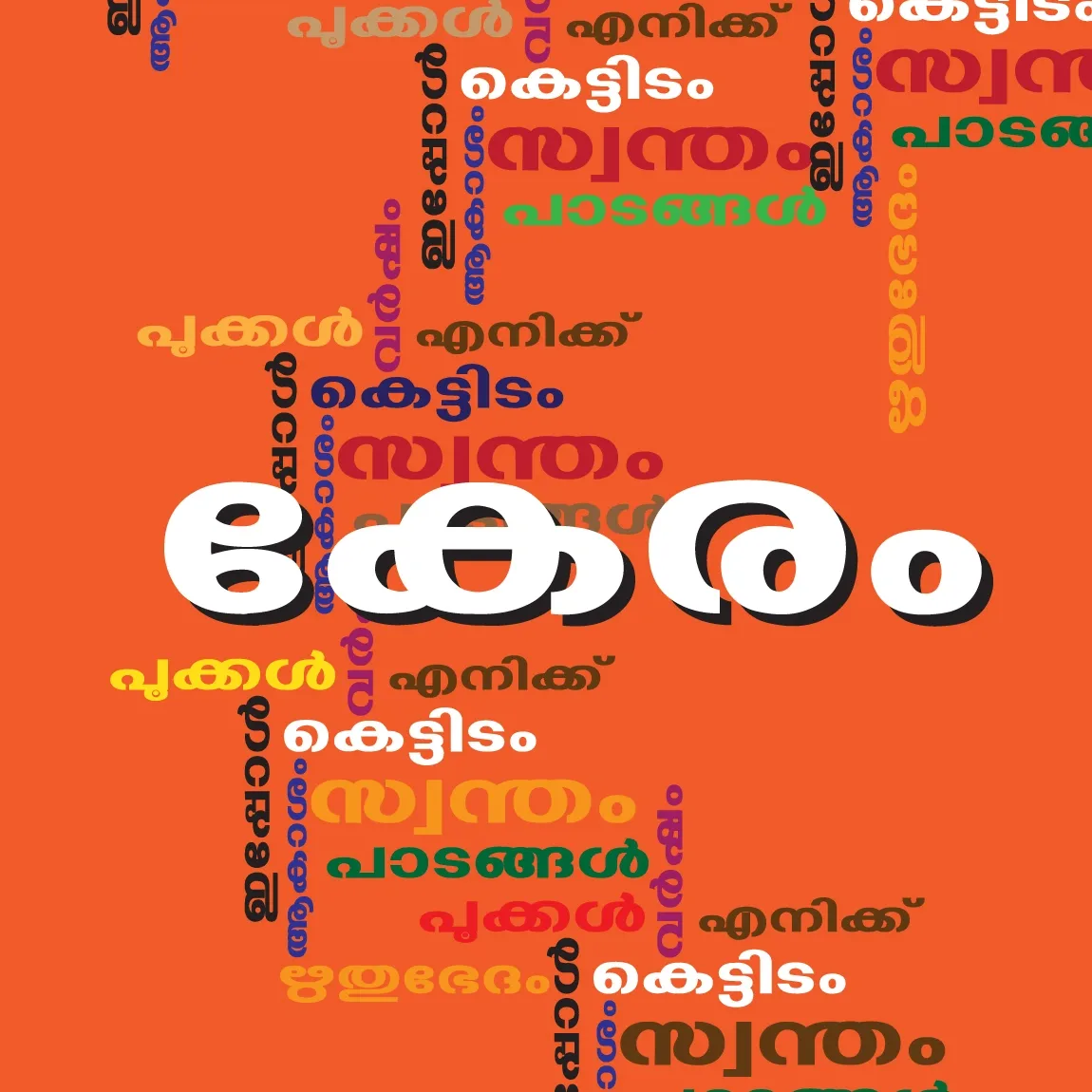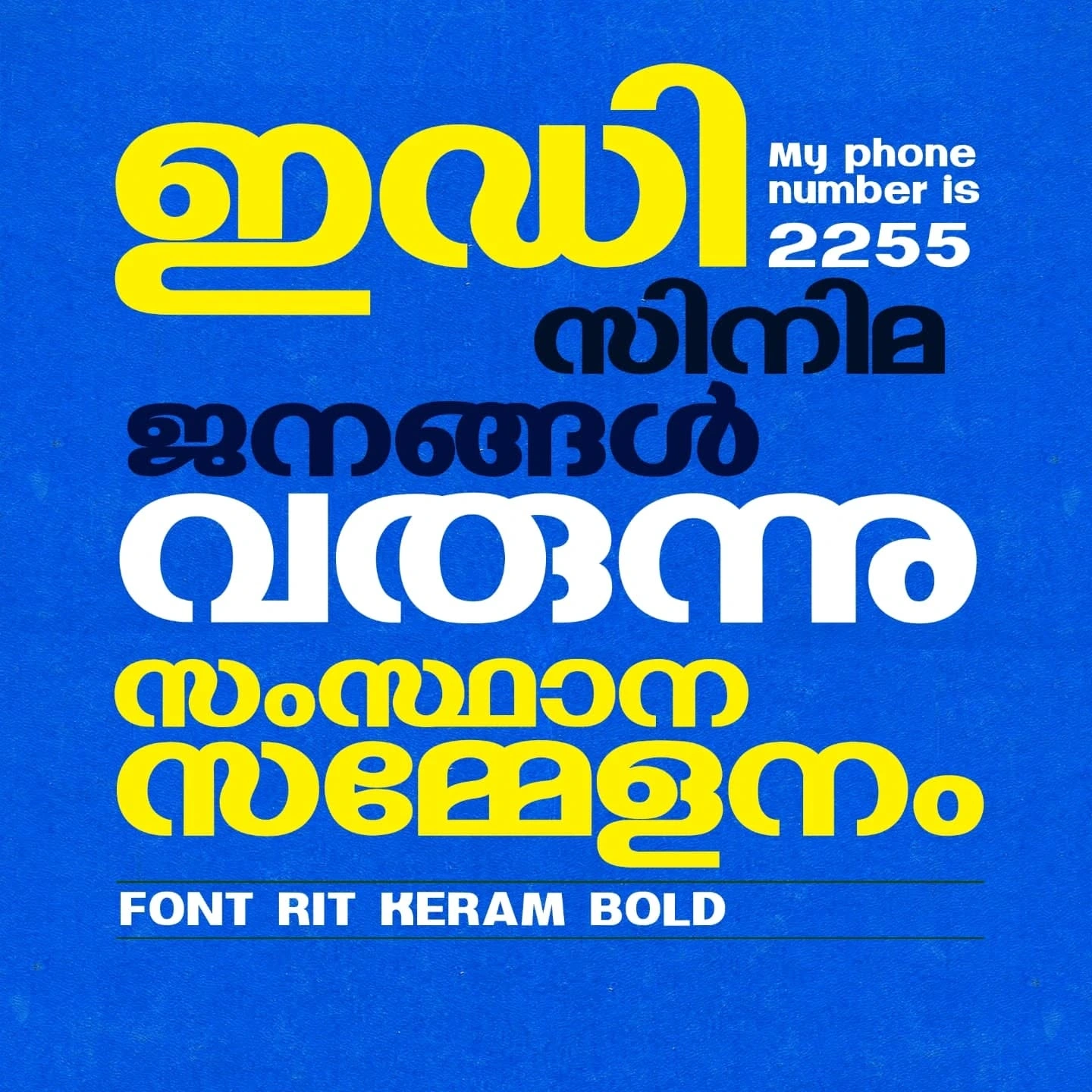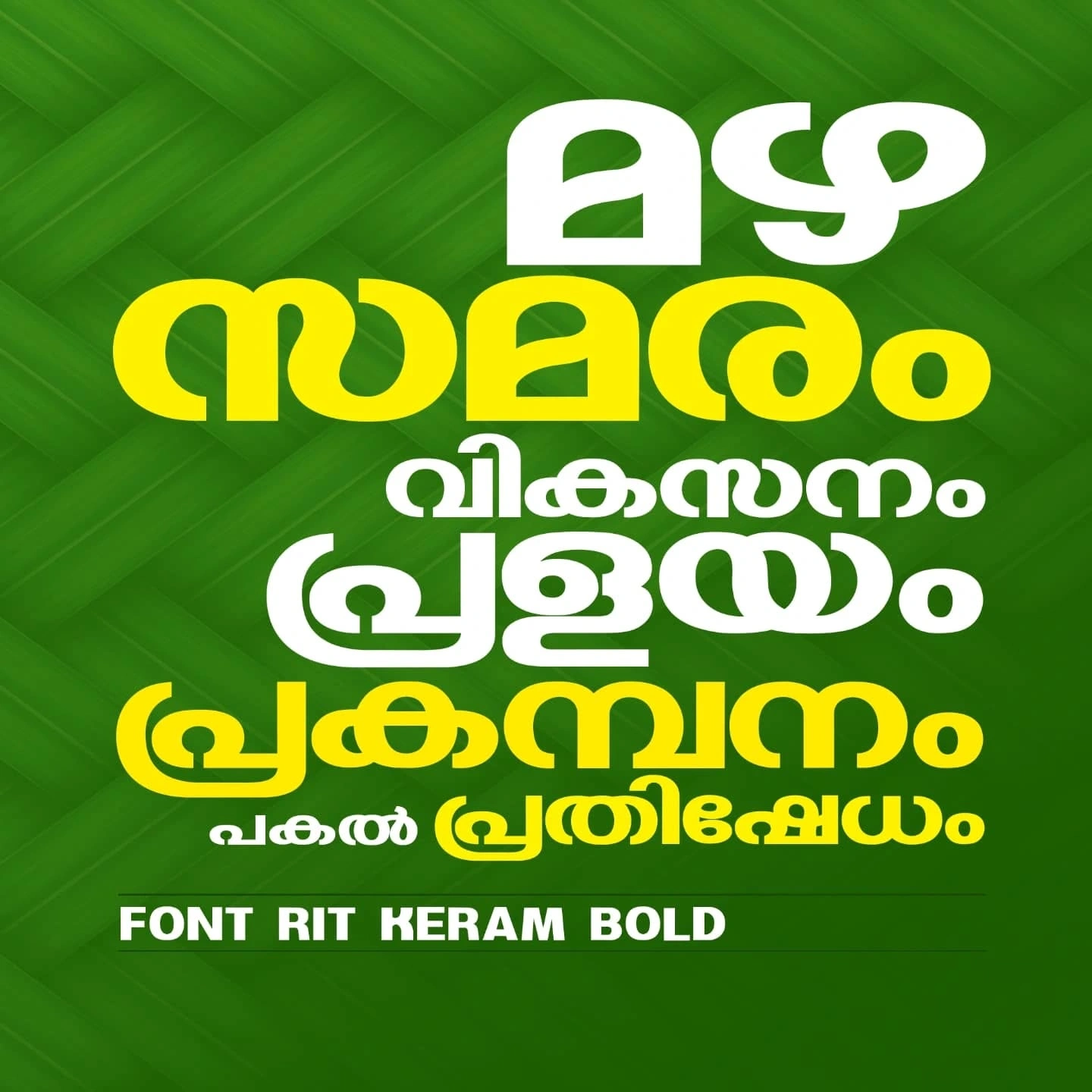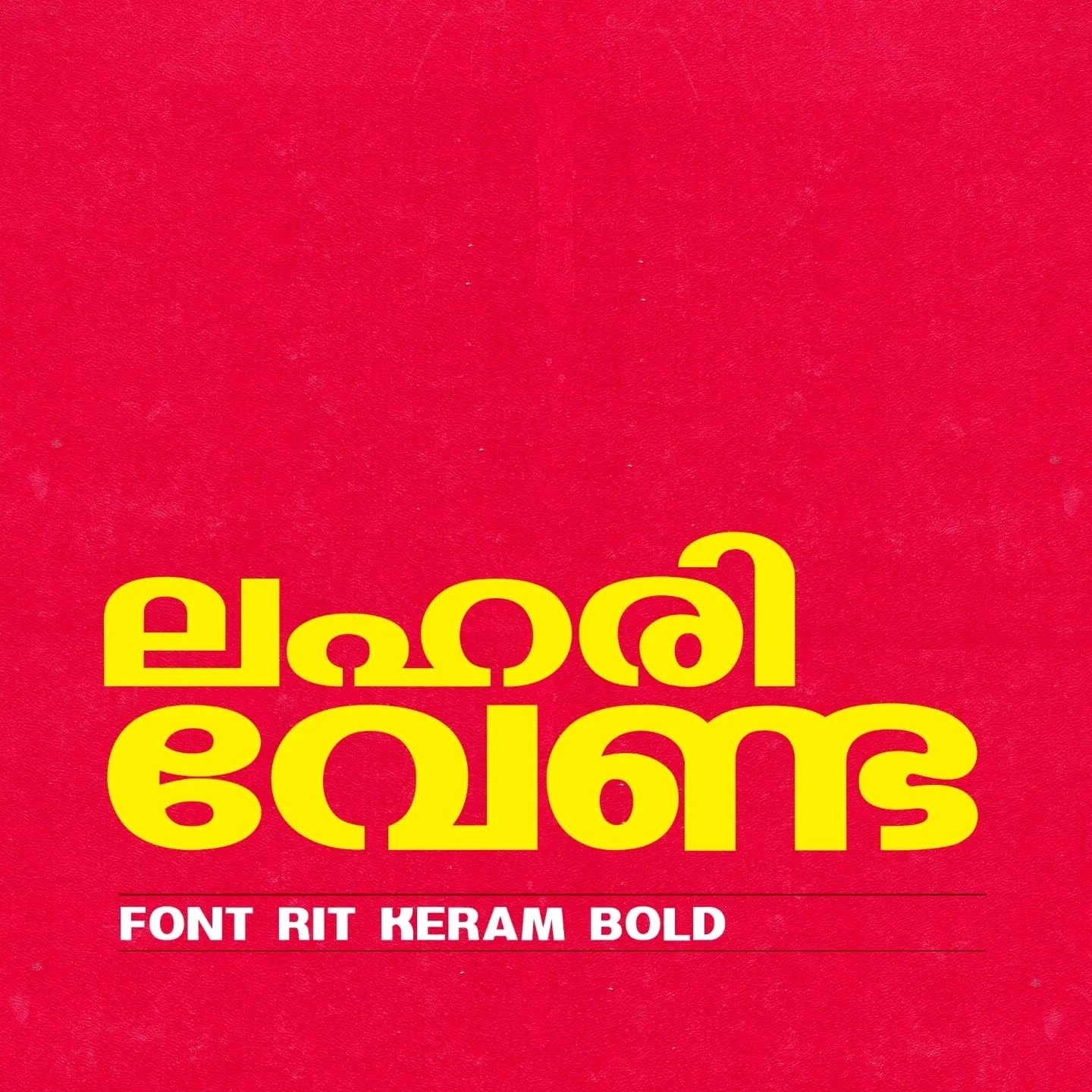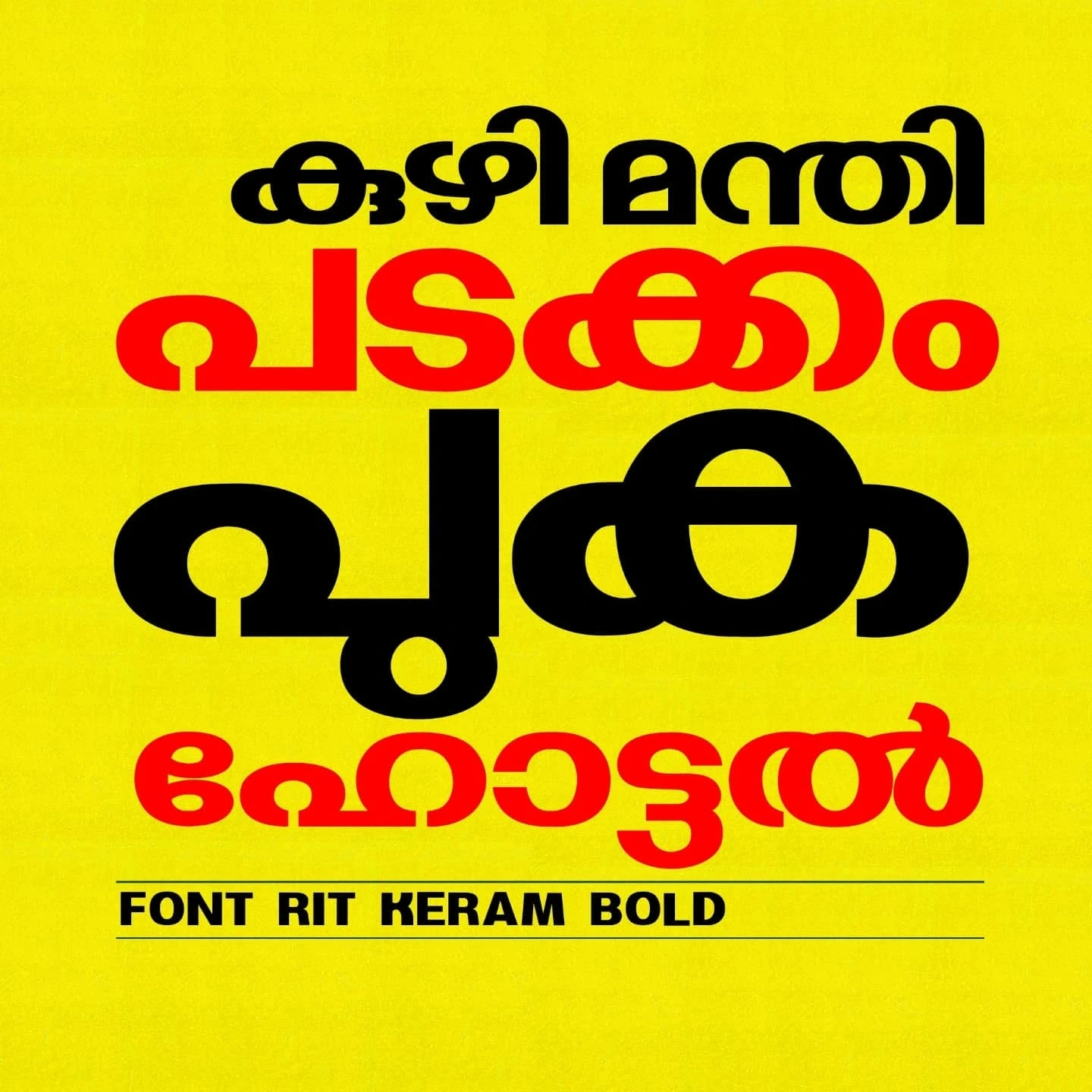
RIT-Keram | Award Winning Malayalam Display Font
മലയാളം ഫോണ്ട് ഡിസൈൻ രംഗത്ത് സായഹ്ന ഫൗണ്ടേഷനും (Sayahna Foundation) കചടതപയും (KaChaTaThaPa) സംയുക്തമായി സംഘടിപ്പിച്ച Open Font Design Competition 2025-ൽ പ്രോത്സാഹന സമ്മാനം (Encouragement Prize) നേടിയ മനോഹരമായ ഒരു ഡിസ്പ്ലേ ഫോണ്ടാണ് RIT-Keram. കണ്ണൂർ സ്വദേശിയായ പ്രഗത്ഭ ഡിസൈനർ സനേഷ് എം.വി (Sanesh MV) ആണ് ഈ ഫോണ്ട് രൂപകല്പന ചെയ്തിരിക്കുന്നത്.
പ്രത്യേകതകൾ:
Unique Design: ബോൾഡ് ആയ അക്ഷരരൂപങ്ങളും വ്യത്യസ്തമായ വളവുകളും ഈ ഫോണ്ടിനെ മറ്റ് ഡിസ്പ്ലേ ഫോണ്ടുകളിൽ നിന്ന് വേറിട്ടു നിർത്തുന്നു.
Award-Winning Style: ഡിസൈൻ മത്സരത്തിൽ അവാർഡ് നേടിയതിനാൽ തന്നെ ഇതിന്റെ ഗുണനിലവാരം ഉറപ്പാണ്. 2025 ഏപ്രിൽ 8-നാണ് ഈ ഫോണ്ട് ഔദ്യോഗികമായി പുറത്തിറങ്ങിയത്.
Versatile Use: സിനിമ പോസ്റ്ററുകൾ, പുസ്തകങ്ങളുടെ കവർ ഡിസൈനുകൾ, സോഷ്യൽ മീഡിയ ഹെഡ്ഡറുകൾ എന്നിവയ്ക്ക് ഒരു പ്രീമിയം ലുക്ക് നൽകാൻ RIT-Keram സഹായിക്കും.